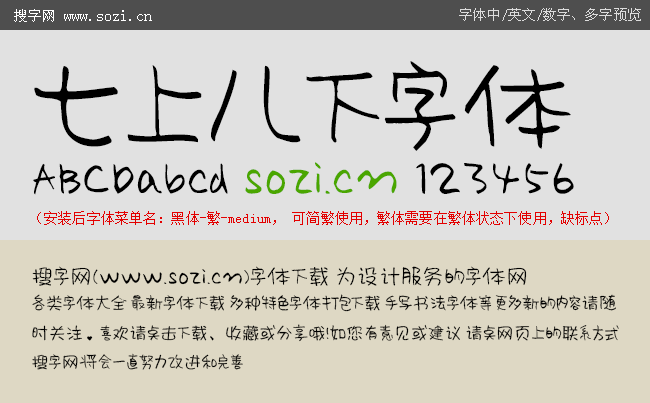
七上八下字體
搜字網(wǎng)給大家提供一款很卡通的手機(jī)中文字體下載。修改者將它命名為七上八下字體,這款手機(jī)字體是仿照兒童手寫風(fēng)格的卡通手寫字體,結(jié)構(gòu)帶有POP字體風(fēng)格,筆畫(huà)粗細(xì)變化更顯趣味性,特別適合喜歡手機(jī)字體個(gè)性一些的朋友在手機(jī)上安裝使用。